Как настроить оптический размер и функции OpenType в CSS
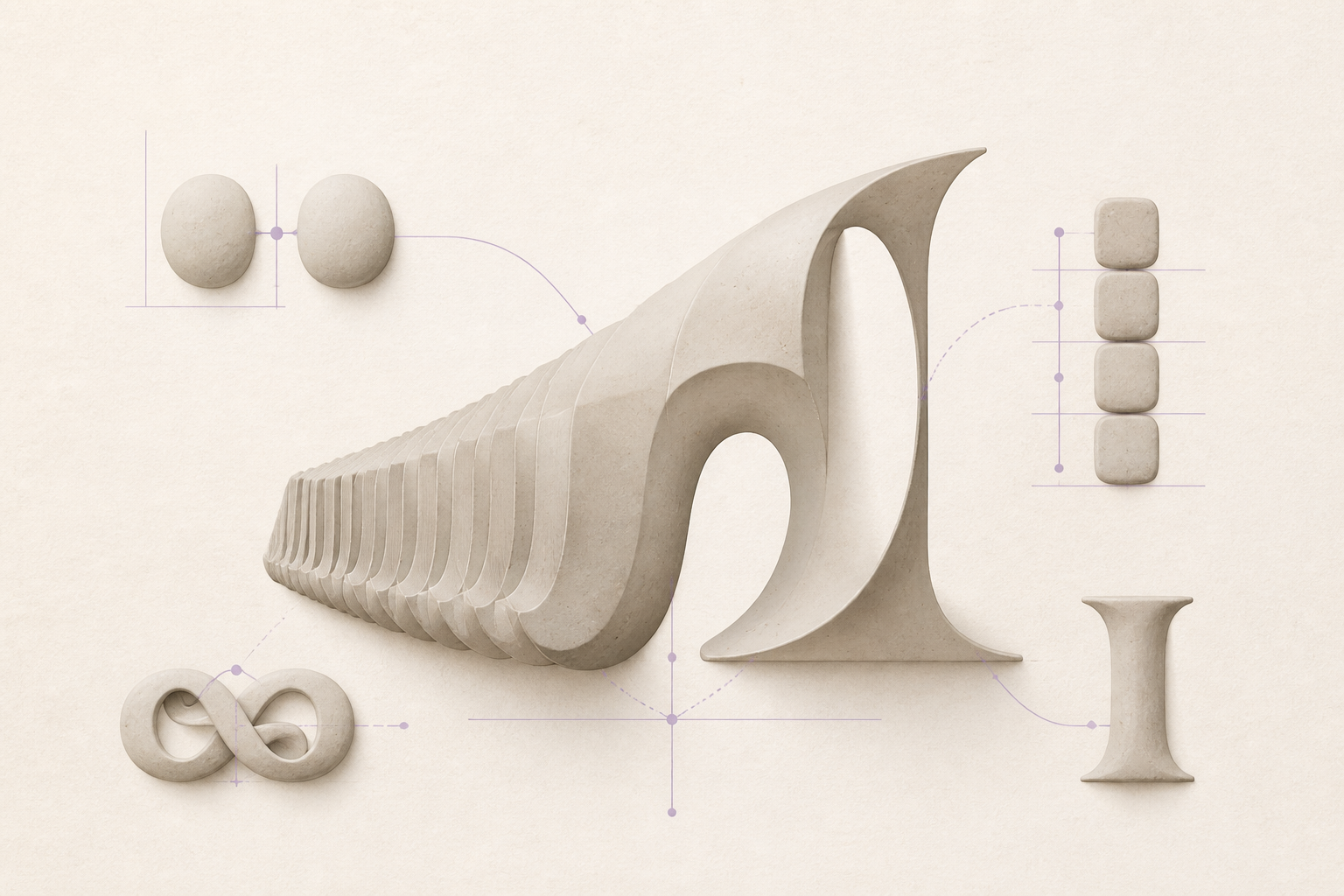
Оптический размер в CSS настраивают свойством font-optical-sizing, а отдельные функции OpenType — свойствами font-variant и font-feature-settings. Автоматический режим подбирает рисунок шрифта под кегль, а явная настройка позволяет управлять лигатурами, кернингом, цифрами, капителью и вариативными осями. Ниже — практическая схема подключения, настройки и проверки.
Актуально на 28 августа 2026 года. Примеры рассчитаны на современную веб-верстку и шрифты, в которых заявлены соответствующие OpenType-функции или вариативные оси. Если конкретный файл шрифта не поддерживает нужную возможность, CSS-свойство не создаст ее искусственно.
Что такое оптический размер шрифта
Оптический размер, или optical size, — это адаптация рисунка шрифта к размеру набора. В маленьком кегле буквы обычно получают более открытые апертуры, увеличенную разборчивость, менее тонкие детали и чуть более свободный ритм. В крупном кегле шрифт может использовать изящные контрасты, плотнее собирать формы и точнее показывать характер гарнитуры. Это не обычное масштабирование, а отдельная логика интерполяции или набор оптических мастеров внутри шрифта.
Вариативные шрифты часто содержат ось opsz. Ее диапазон задает автор шрифта, поэтому значения вроде 8, 14 или 72 не являются универсальным стандартом для всех гарнитур. В статических семействах оптические размеры могут поставляться отдельными файлами: например, для текста, подзаголовков и дисплейного набора. Перед версткой важно выяснить, действительно ли выбранный файл поддерживает opsz.
Как устроены функции OpenType в веб-шрифте
OpenType — это формат шрифта, который может хранить не только контуры букв, но и правила их замены и позиционирования. К таким правилам относятся стандартные и декоративные лигатуры, контекстные альтернативы, капитель, дроби, порядковые обозначения, табличные цифры и кернинг. Браузер применяет эти функции через CSS, но результат зависит от поддержки функции в самом шрифте и от возможностей конкретного движка.
Вариативные оси и их назначение
У вариативного шрифта могут быть стандартные оси wght для насыщенности, wdth для ширины, slnt для наклона, ital для перехода между прямым и курсивным начертанием и opsz для оптического размера. Также встречаются пользовательские оси с четырехсимвольными тегами, например GRAD для градации насыщенности. Диапазоны и поведение осей определяет создатель гарнитуры, поэтому не следует переносить значения из одного шрифта в другой без проверки.
Высокоуровневые и низкоуровневые свойства
Свойства font-optical-sizing, font-variant-numeric и font-variant-ligatures описывают типографическую задачу понятными CSS-значениями. Свойство font-feature-settings обращается непосредственно к OpenType-тегам, например liga, kern или tnum. Практичное правило такое: сначала используйте высокоуровневое свойство, а font-feature-settings оставляйте для функции, у которой нет удобного стандартизированного аналога или требуется точный контроль.
Подключите шрифт и проверьте его возможности
Шаг 1. Подключите правильный файл
Начните с объявления @font-face и укажите формат файла, начертание и диапазон насыщенности, если это вариативный шрифт. Пример: @font-face { font-family: Editorial; src: url('/fonts/editorial-var.woff2') format('woff2'); font-style: normal; font-weight: 300 800; font-display: swap; }. После подключения проверьте, что браузер действительно использует этот файл, а не системный fallback.
Шаг 2. Найдите оси и OpenType-теги
Посмотрите документацию гарнитуры или сведения, которые предоставляет инструмент инспекции шрифта. Для оптического размера ищите ось opsz и ее минимальное и максимальное значения. Для функций OpenType проверяйте поддерживаемые теги: liga отвечает за стандартные лигатуры, dlig — за декоративные, kern — за кернинг, onum — за старостильные цифры, tnum — за табличные цифры, frac — за дроби.
Настройте оптический размер через font-optical-sizing
Для большинства проектов достаточно свойства font-optical-sizing: auto. В этом режиме браузер передает шрифту текущий размер текста, а вариативная ось opsz выбирает соответствующий рисунок. Если шрифт поддерживает optical sizing, базовое правило может выглядеть так: body { font-family: Editorial, sans-serif; font-optical-sizing: auto; }. Это хороший старт для длинного текста, интерфейсов и адаптивных макетов.
Значение none отключает автоматическую оптическую настройку. Оно полезно, когда нужно сохранить единый рисунок во всех размерах, сравнить режимы в тесте или вручную управлять осью. Отключение не делает шрифт «неправильным», но может ухудшить читаемость мелкого текста, если гарнитура проектировалась с заметной разницей между текстовым и дисплейным режимами.
Когда нужен ручной контроль оси opsz
Ручное значение применяют в арт-дирекшене, брендинге и сложной типографической системе, где рисунок должен быть предсказуемым независимо от кегля. Пример: .display { font-optical-sizing: none; font-variation-settings: 'opsz' 72, 'wght' 650; }. Число 72 допустимо только в том случае, если оно входит в диапазон конкретного шрифта. Для основного текста чаще безопаснее оставить auto.
Не смешивайте ручную настройку без необходимости. Если одновременно задать font-optical-sizing: auto и font-variation-settings: 'opsz' 72, явное значение оси может стать фактическим приоритетом для opsz. В дизайн-системе заранее выберите один принцип: автоматическая адаптация для текста или фиксированные значения для определенных типографических ролей.
Включите кернинг и стандартные лигатуры
Кернинг изменяет расстояние между конкретными парами букв, чтобы визуальный интервал выглядел равномерным. Для обычного текста используйте font-kerning: normal или auto. Значение none отключает кернинг и может быть оправдано только в специальной графике, техническом интерфейсе или при отладке. Если гарнитура содержит качественную таблицу кернинга, отключать ее без причины не стоит.
Стандартные лигатуры объединяют некоторые последовательности знаков в одну глифовую форму. В веб-наборе обычно достаточно font-variant-ligatures: common-ligatures или значения по умолчанию. Декоративные лигатуры включайте осторожно: font-variant-ligatures: discretionary-ligatures может изменить узнаваемость сочетаний и не всегда подходит для интерфейсного текста, юридических документов и числовых данных.
Настройте цифры, дроби и капитель
Цифры требуют отдельной настройки, потому что разные сценарии предъявляют разные требования. В редакционном тексте часто уместны пропорциональные цифры, а в таблицах, счетах и интерфейсах сравнения — табличные. Для этого используйте font-variant-numeric: proportional-nums или font-variant-numeric: tabular-nums. Начертание цифр можно дополнительно выбрать как lining-nums или oldstyle-nums.
Дроби и специальные числовые формы включают только там, где они улучшают набор. Например, font-variant-numeric: diagonal-fractions может превратить последовательность чисел в диагональную дробь, если функция есть в шрифте. Для технической информации полезны slashed-zero и ordinal, но их не следует включать глобально: ноль с косой чертой или порядковый суффикс нужны не каждому тексту.
Капитель — это не просто уменьшенные прописные буквы. Настоящая small caps создается отдельными глифами, рассчитанными на малый размер и согласованными по толщине с текстом. Используйте font-variant-caps: small-caps для аббревиатур, рубрикации или редакционных акцентов, но проверяйте кириллицу: не каждый шрифт содержит полноценную капитель для русского алфавита.
Соберите практическую типографическую систему
Вместо набора разрозненных свойств создайте несколько типографических ролей. Для body задайте автоматический оптический размер, обычный кернинг и стандартные лигатуры. Для table примените табличные цифры. Для display при необходимости зафиксируйте opsz и отдельно проверьте интервалы между крупными буквами. Такой подход упрощает поддержку и не заставляет разработчиков повторять длинные объявления в каждом компоненте.
Пример системы: body { font-optical-sizing: auto; font-kerning: normal; font-variant-ligatures: common-ligatures; } .data { font-variant-numeric: tabular-nums lining-nums; } .caption { font-variant-caps: small-caps; letter-spacing: 0.04em; }. Межбуквенный интервал для капители подбирайте визуально: универсального значения для всех гарнитур нет.
Если нужна функция без удобного CSS-аналога, используйте font-feature-settings: 'ss01' 1, где ss01 — стилистический набор, определенный автором шрифта. Название и номер набора нельзя угадывать: ss01 в одной гарнитуре может включать альтернативную форму буквы, а в другой — другой рисунок цифр. Документируйте такие решения в дизайн-системе.
Проверьте результат в реальном макете
Тестируйте OpenType-функции не на одной строке, а на реальном наборе: длинном абзаце, заголовке, таблице, датах, денежных значениях, дробях и кириллических словах. Сравнивайте несколько кеглей и начертаний. Оптическая настройка может выглядеть убедительно в заголовке, но давать слишком плотный или слишком светлый ритм в мелком тексте.
- Откройте страницу в целевых браузерах и убедитесь, что загружается нужный файл шрифта.
- Сравните auto и none для нескольких размеров текста, включая самый маленький допустимый кегль.
- Проверьте пары букв, знаки препинания, цифры, валюты, дроби и аббревиатуры.
- Сверьте табличные цифры в колонках и пропорциональные цифры в обычном тексте.
- Проверьте переносы, ширину строк и высоту блока после включения лигатур или альтернатив.
- Зафиксируйте выбранные свойства в токенах или классах дизайн-системы.
Частые ошибки при настройке OpenType
- Включать все функции сразу. Полный набор OpenType-возможностей не делает текст автоматически лучше: декоративные лигатуры, капитель и альтернативы должны соответствовать задаче.
- Задавать неподходящий диапазон оси. Значение opsz или wdth вне диапазона конкретного шрифта может быть ограничено, проигнорировано или дать непредсказуемый визуальный результат.
- Использовать font-feature-settings для всего подряд. Низкоуровневые теги сложнее читать и поддерживать, поэтому для цифр, кернинга и лигатур предпочтительнее font-variant и font-kerning.
- Проверять только латиницу. Поддержка OpenType-функции для латинских глифов не означает, что она реализована для кириллицы.
- Путать оптический размер с насыщенностью. Ось opsz меняет рисунок под кегль, а wght меняет вес; они решают разные задачи и могут применяться одновременно.
- Забывать о fallback-шрифте. Системная замена может не иметь нужных осей и функций, поэтому проверяйте поведение при задержке загрузки и ошибке запроса.
- Файл шрифта содержит ось opsz, если используется ручной или автоматический optical sizing.
- Для каждой функции определена понятная типографическая задача.
- Основной текст проверен в нескольких кеглях и на кириллице.
- Таблицы используют tabular-nums, когда важна вертикальная выравненность чисел.
- Декоративные лигатуры и стилистические наборы не включены глобально без необходимости.
- Fallback-сценарий не ломает ширину строк и композицию.
- CSS-правила вынесены в понятные классы, токены или компоненты.
- Результат проверен на реальном контенте, а не только на демонстрационной строке.
Что делает font-optical-sizing: auto?
Свойство включает автоматическую подстройку оптического размера, если шрифт поддерживает соответствующую ось. Браузер учитывает текущий размер текста и выбирает рисунок, рассчитанный на этот диапазон. Если в файле нет opsz, видимого эффекта от auto не будет.
Чем оптический размер отличается от font-size?
font-size меняет размер набора, а optical sizing выбирает или интерполирует рисунок шрифта для этого размера. При увеличении кегля буквы не только становятся крупнее: могут измениться контраст, пропорции, открытость форм и плотность деталей. Поэтому два одинаковых font-size могут выглядеть по-разному в auto и none.
Нужно ли всегда включать font-kerning: normal?
Для обычного текста кернинг обычно стоит оставить включенным или использовать auto. Качественная таблица кернинга выравнивает визуальные интервалы между парами знаков и особенно заметна в заголовках. Отключение оправдано только для специальных случаев, когда ровная механическая сетка важнее естественного рисунка слова.
Можно ли включить OpenType-функцию без вариативного шрифта?
Да. Вариативность и OpenType-функции — разные возможности. Статический шрифт может содержать лигатуры, капитель, табличные цифры или дроби, даже если у него нет вариативных осей. Проверяйте таблицы и документацию конкретного файла, а не только его расширение или название семейства.
Когда использовать font-feature-settings?
Используйте font-feature-settings, когда нужно обратиться к конкретному OpenType-тегу, например к стилистическому набору ss01 или уникальной функции гарнитуры. Для стандартных задач лучше подходят font-variant-ligatures, font-variant-numeric, font-variant-caps и font-kerning: они понятнее, легче документируются и точнее выражают намерение верстки.
Почему оптический размер не меняется в браузере?
Наиболее частые причины — в файле нет оси opsz, браузер использует fallback, значение переопределено font-variation-settings или различие между мастерами слишком небольшое для выбранного кегля. Проверьте загруженный файл в инструментах разработчика, диапазон оси и итоговые вычисленные CSS-свойства.
Подходит ли optical sizing для интерфейсов?
Да, особенно для интерфейсов с разными уровнями текста: мелкими подписями, обычными описаниями и крупными заголовками. Но интерфейс нужно тестировать на реальных состояниях, включая кнопки, таблицы, длинные названия и узкие экраны. Если автоматическая настройка меняет ширину компонентов слишком заметно, зафиксируйте типографические роли или выберите другой шрифт.
Начинайте с font-optical-sizing: auto, если вариативный шрифт содержит opsz, и добавляйте остальные OpenType-функции только под конкретные задачи: кернинг для пар букв, табличные цифры для колонок, капитель для редакционных акцентов, лигатуры и альтернативы для особого характера набора. Проверка на реальном контенте важнее формального включения всех возможностей.